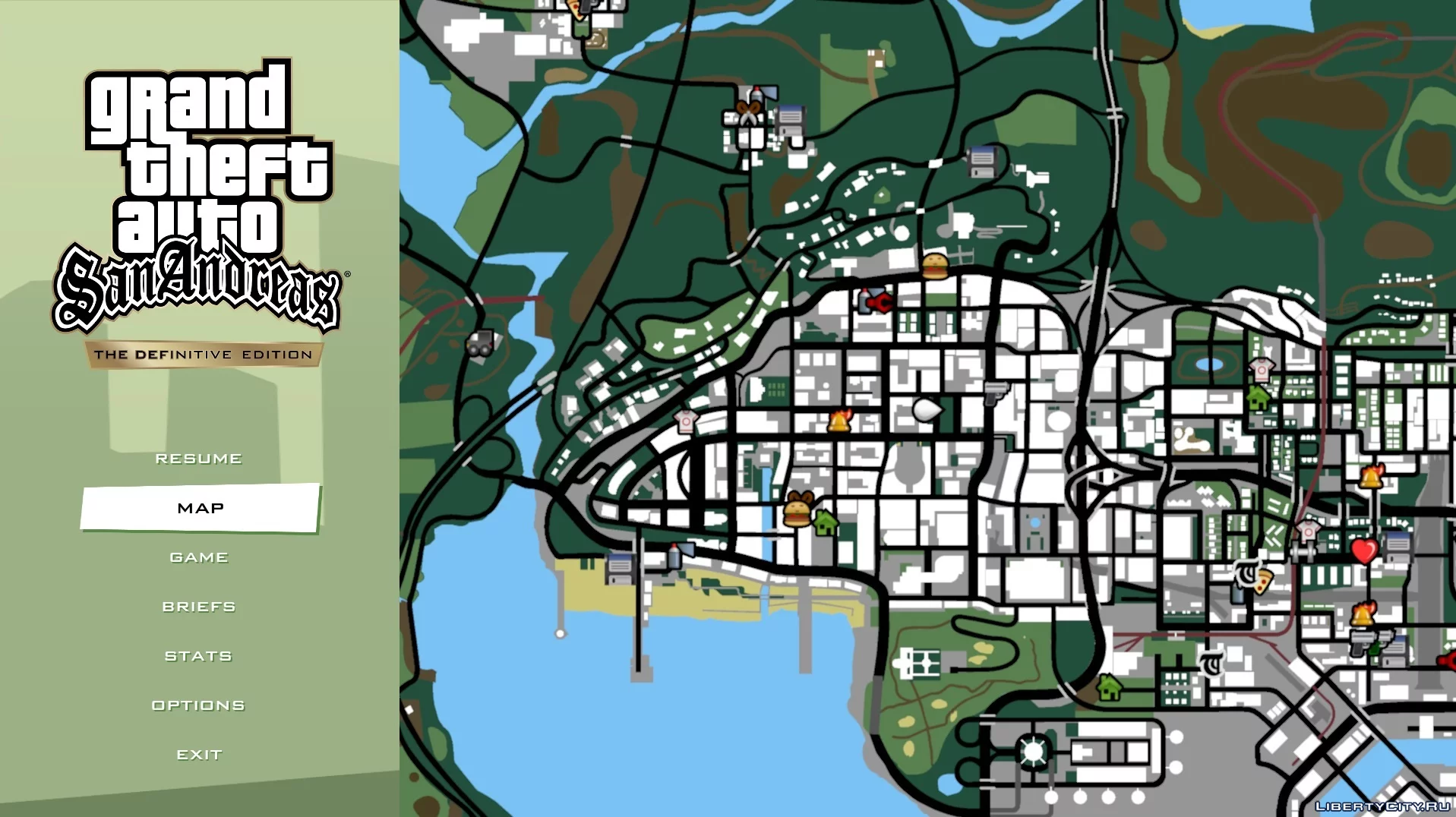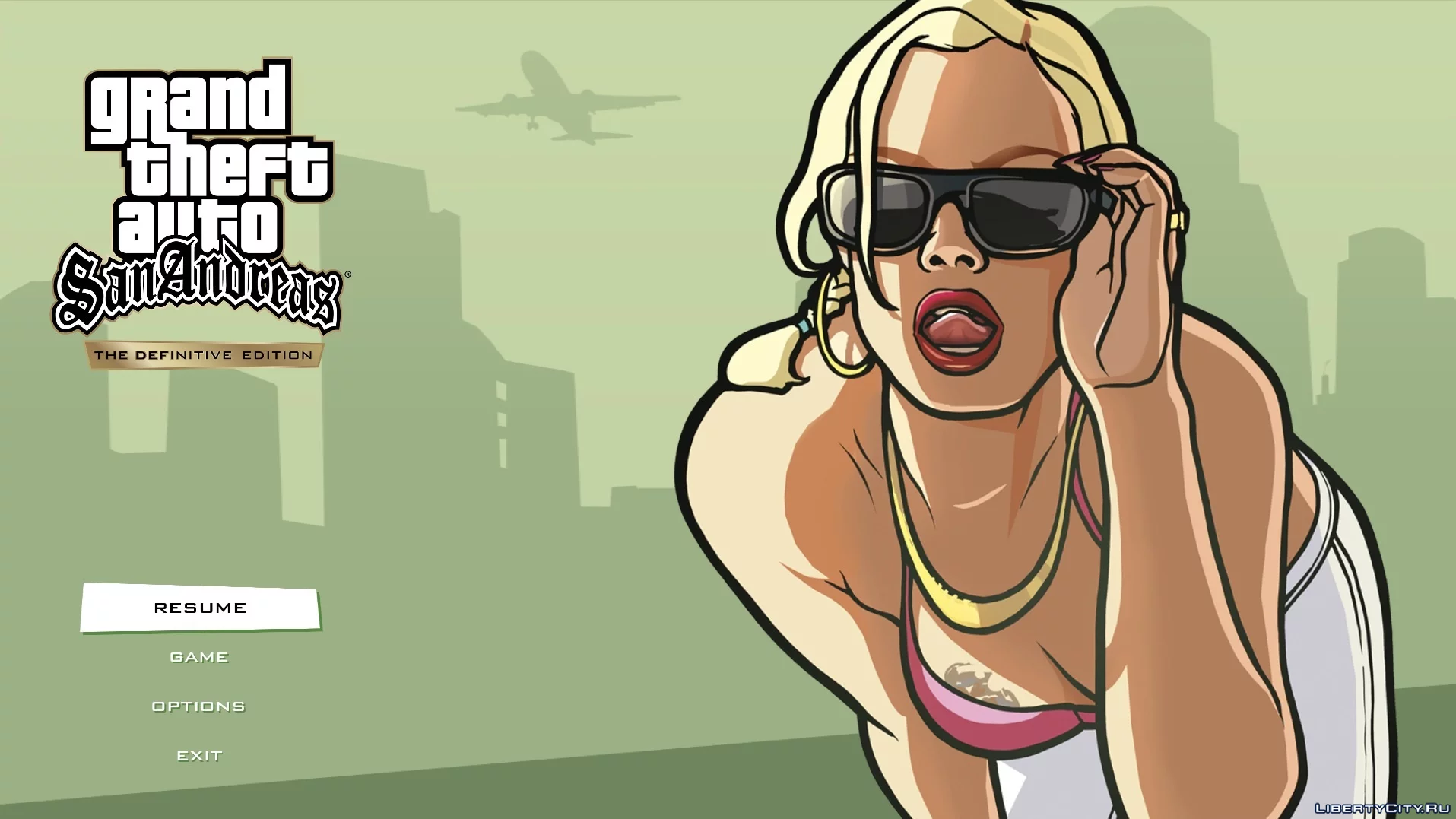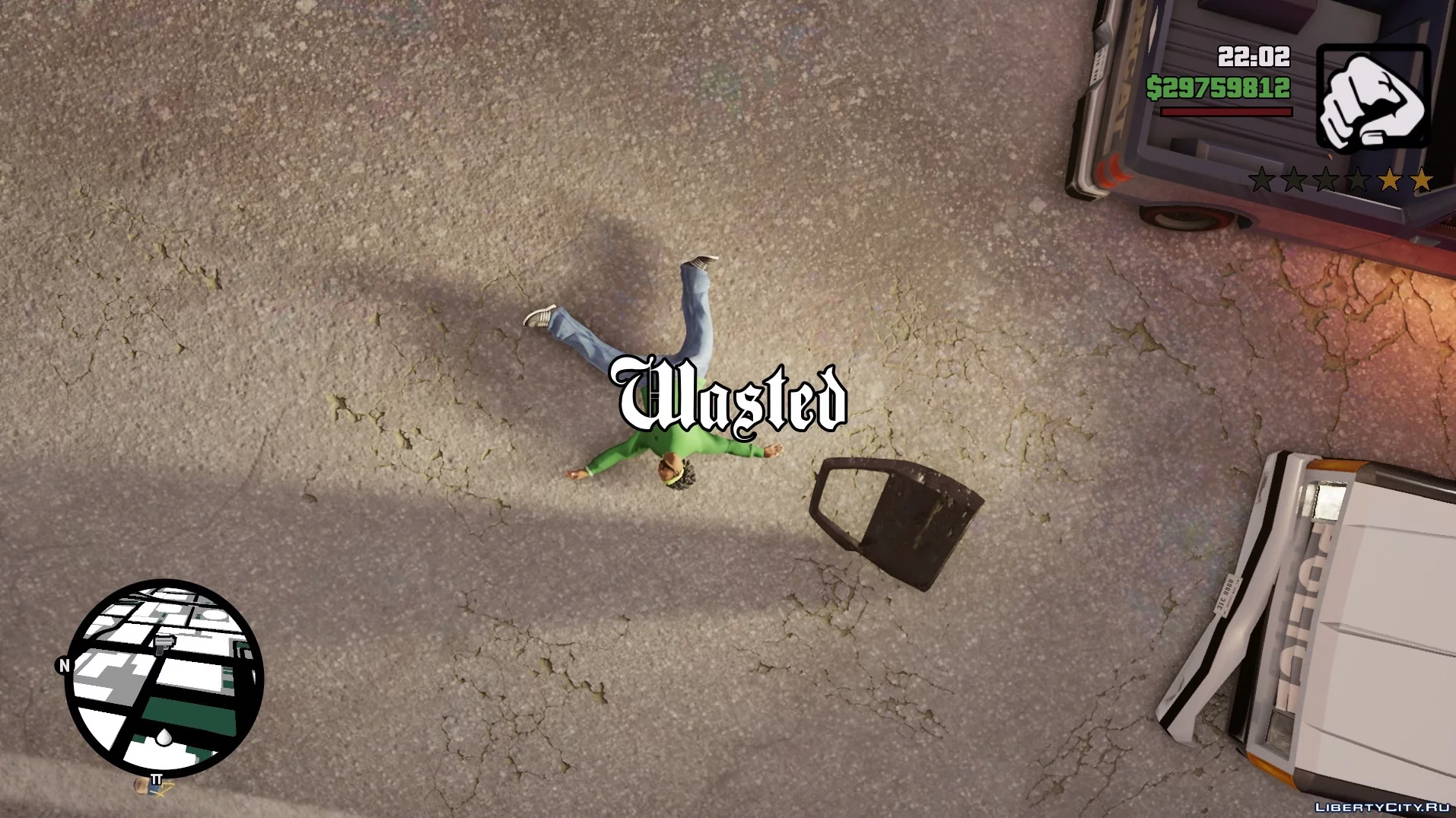
Классический шрифт [GTA 3, VC, SA]
[GTA Trilogy] Classic Fonts (letras da versão clássica).
Данная модификация меняет шрифт в трилогии, делая его похожим на тот, который используется в классических версиях игр. Также мод подходит для GTA 3 и Vice City.